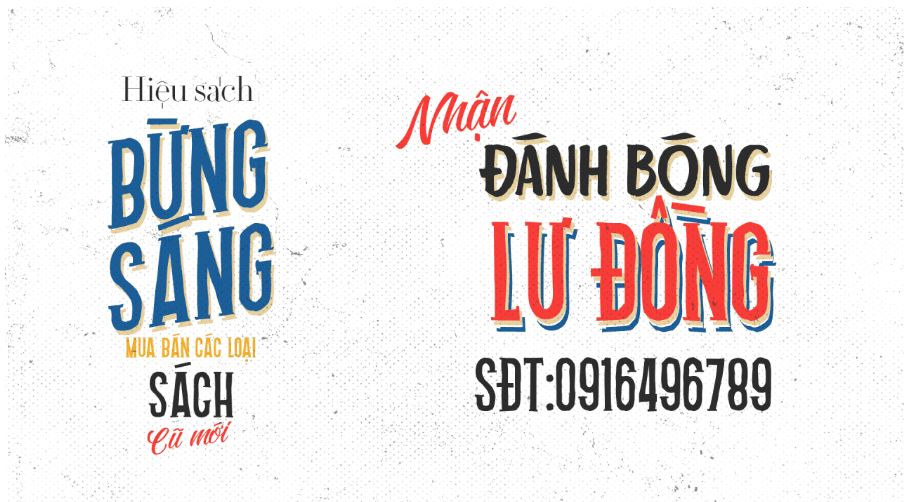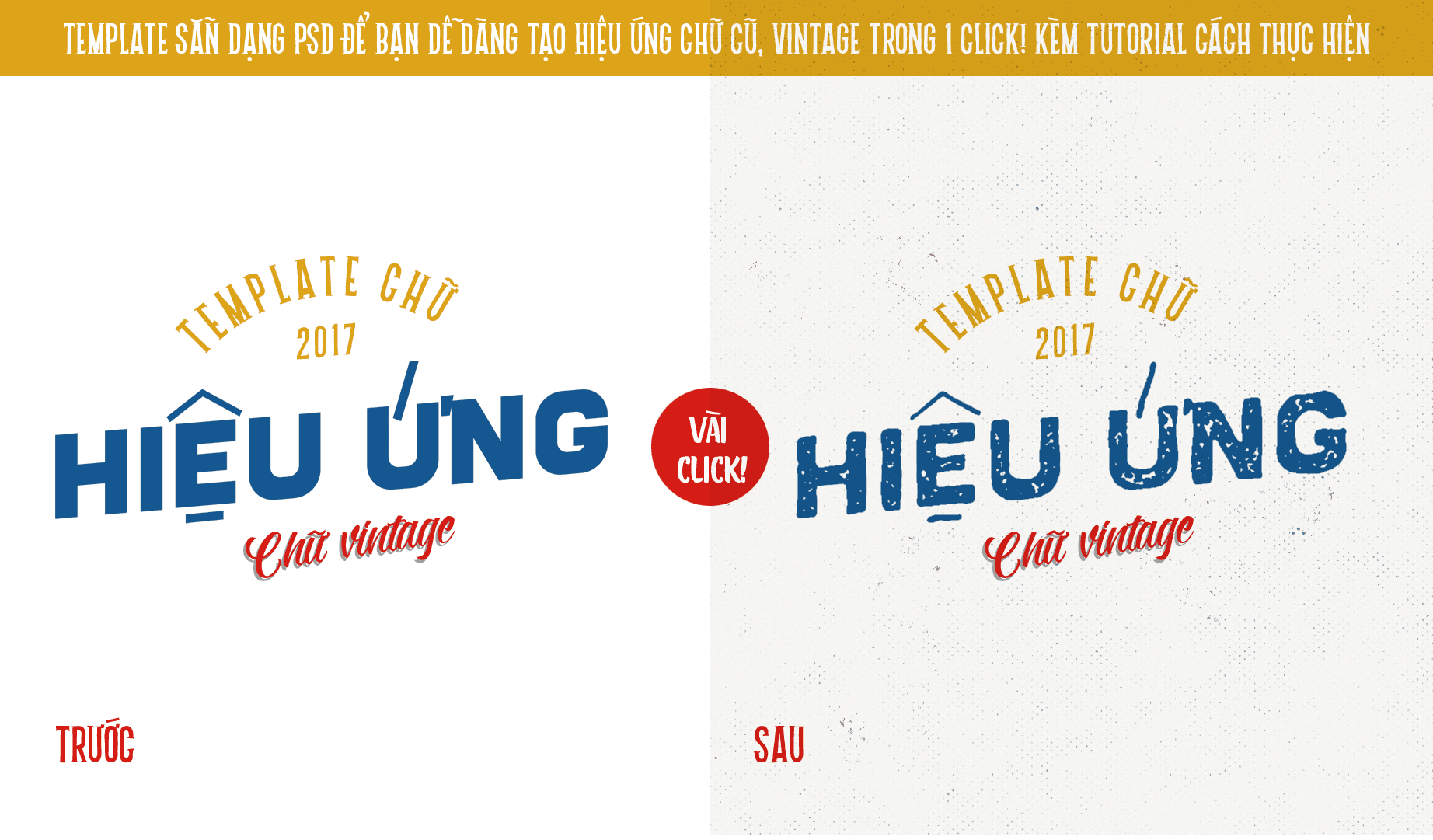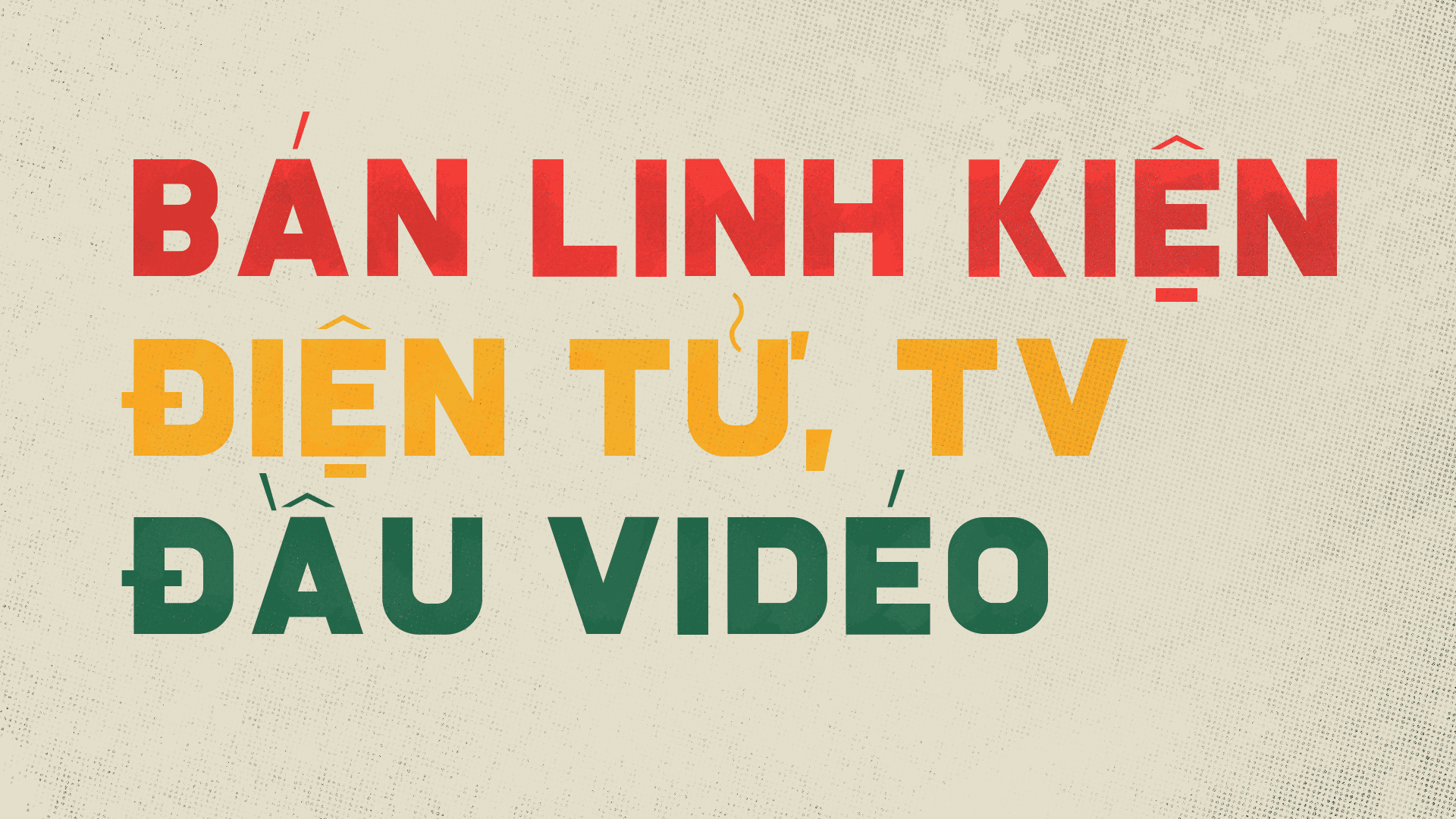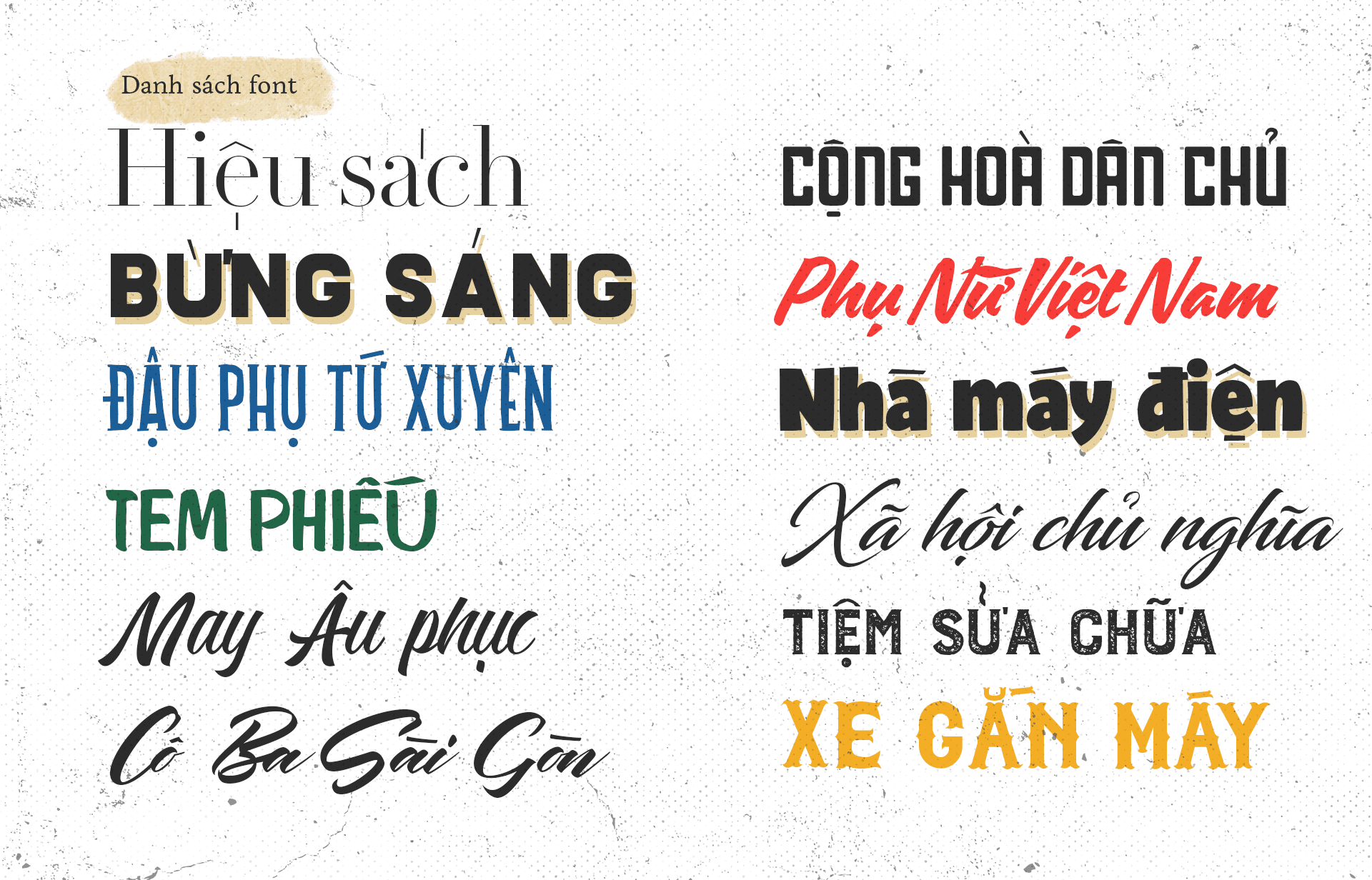
Mình luôn thấy hứng thú với những biển hiệu vẽ tay, gần đây nhất là trào lưu “Vịt lộn vịt dữa cút lộn” gây sóng gió cộng đồng mạng. Nhưng những biển hiệu ngày nay hầu hết đều được in trên máy với những font chữ việt hoá lỗi thời, cách bỏ dấu đơn điệu, mất đi nét đẹp của những biển hiệu đầy tính nghệ thuật thời xưa. Bộ font do chính tay mình chọn lọc và việt hoá theo phong cách bỏ dấu xưa, phù hợp với các loại poster, bảng biển quảng cáo đậm chất Việt Nam. Tư liệu tham khảo đến từ luuchu.com.
Bộ font này chỉ có tại iCiel mà không có ở nơi nào khác. Mình phải làm không ngừng nghỉ trong gần 2 tháng, nghiên cứu từng cách bỏ dấu sao cho phù hợp nhất.
Bộ font này bao gồm:
– 12 font chữ dành cho tựa đề.
– 3 font chữ serif dành cho body text. Các font này đều có tính năng smallcaps tự động.